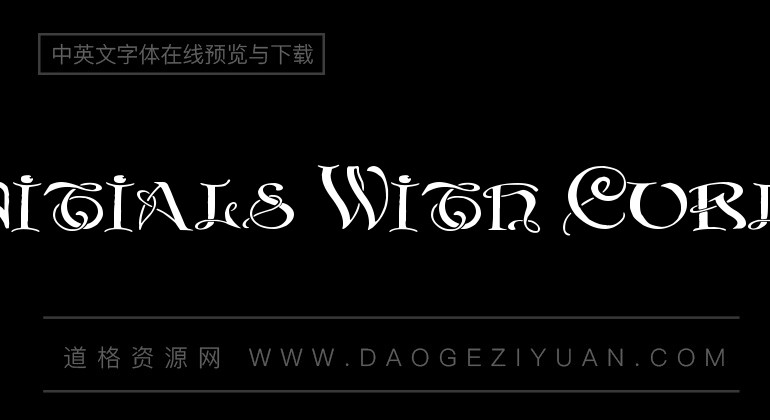
Initials With Curls
? Initials With Curls字体是一种古典的手写字体,它由美国设计师Julie Gafert创作,于2020年发布。它的字体特点是充满活力的曲线,拥有优雅的外观,给人以柔和的感觉。它的字形以及细节都是精心设计的,能够提供一种自然而精美的视觉效果。该字体可以用于各种商业和个人应用,如标志,海报,印刷品,广告,网页,礼品和其他设计项目。
Initials With Curls是一款非常不错的手写艺术字体,具有很好的视觉感,适合于文化类的宣传设计、商业类品牌的广告和产品包装设计以及个性化文字排版等较多场景。